Nếu bạn thường sử dụng nền tảng TikTok để giải trí chắc hẳn bạn sẽ biết đến ứng dụng Capcut. Capcut được ra đời nhằm hỗ trợ việc dựng các video theo template đa dạng cùng với mọi thể lại nhạc nền cuốn hút. Không dừng lại ở đó, khi chỉnh sửa video trên TikTok người dùng còn có thể thêm văn bản trực tiếp vào video. Vì vậy, nội dung bài viết sau đây sẽ giới thiệu 8 font chữ Capcut thời thượng giúp các video của bạn thêm hấp dẫn.
Các font chữ Capcut có tính thẩm mỹ cao
Để tăng độ thẩm mỹ nhưng vẫn đảm bảo được tính chuyên nghiệp của sản phẩm video hãy tìm một số lựa chọn những font chữ mang hơi hướng sang trọng. Sau đây là 8 font chữ Capcut đạt đủ tiêu chí mà chúng tôi muốn giới thiệu đến bạn.
1. Vogue
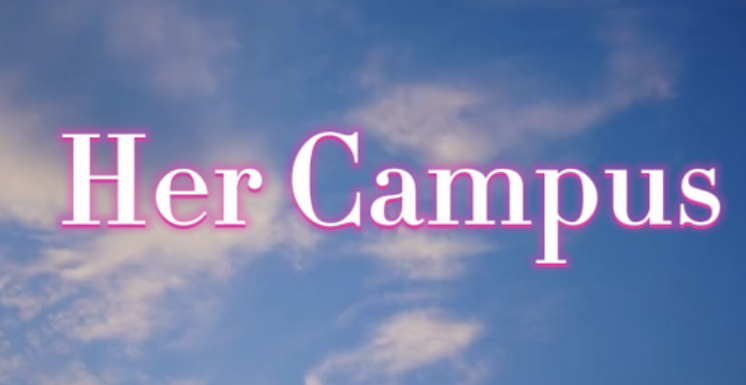
Font chữ Capcut này được nâng thẳng từ bìa tạp chí. Còn cách nào tốt hơn để liên kết thương hiệu của bạn với sự rung cảm thời trang cao cấp từ font chữ mang tên Vogue?
2. Nicolas Cochin LT Pro
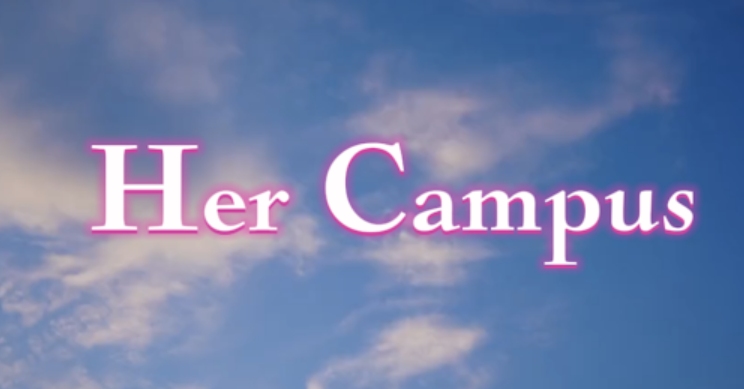
Font chữ này của Capcut mang đến cảm giác như một bộ phim Y2K các năm hai nghìn và phong cách này cũng đang trở lại xu hướng gần đây.
3. Brown Vokly
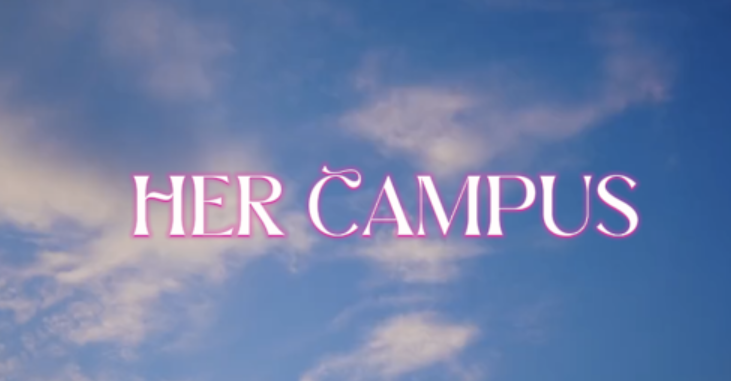
Lựa chọn tiếp theo này mang đến sực tinh tế . Đây là một lựa chọn hoàn hảo nếu phong cách của bạn thiên về khía cạnh thú vị và sôi nổi. Bên cạnh đó font chữ Capcut này vẫn cực kỳ dễ đọc trên màn hình nhỏ!
Những font chữ làm nổi bật câu chuyện
Tất cả chúng ta đều có câu chuyện cần được kể. Nhưng các video dài dòng có thể gặp bất lợi nghiêm trọng nếu không có lựa chọn font chữ phù hợp. Sau đây sẽ là những font chữ Capcut tạo ra sự cân bằng phù hợp bằng cách dễ nhìn nhưng vẫn cho phép một số cá tính tỏa sáng
1. It Clearface Pro
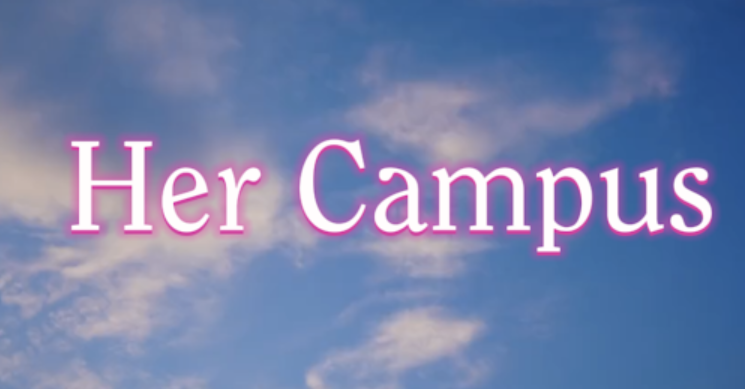
Font chữ Capcut này cực kỳ rõ ràng. Vì vậy nó sẽ không làm mất tập trung vào thông điệp của bạn nhưng vẫn tạo ấn tượng rằng bạn là người dễ gần và vui vẻ.
2. Shirkhand
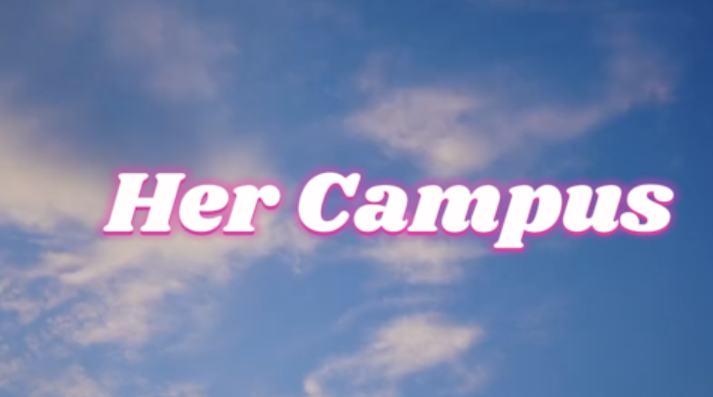
Tiếp theo là font chữ có tên Shirkhand thiên về khía cạnh sáng tạo. Bên cạnh đó font chữ này mang nét nữ tính tinh tế!
3. Helium
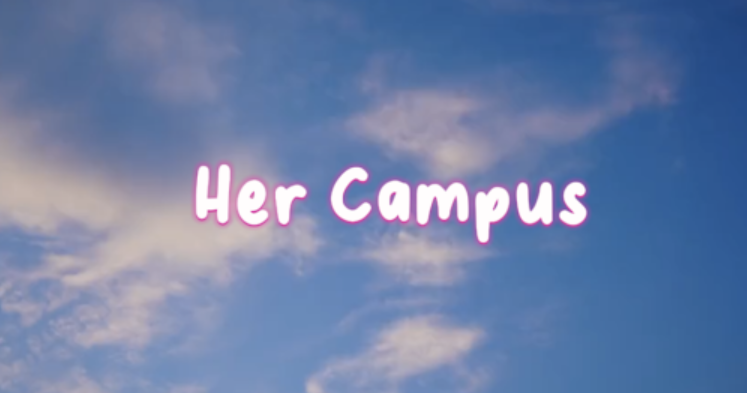
Đây là font chữ nhận được sự ưa chuộng của người dùng. Nó mang lại ấn tượng về chữ viết tay mà trông không quá trẻ con. Đây là một cách tuyệt vời để làm nội dung video có vẻ thực tế và hấp dẫn.
Font chữ mang cảm giác hồi hộp
Nếu bạn đang cố gắng thu hút đám đông trên TikTok, bạn có thể muốn thứ gì đó có thêm một chút gia vị. Hai font chữ Capcut sau đây sẽ khiến video của bạn không trở nên quá phô trương, nhưng lại bổ sung một lượng vừa đủ sự tinh tế.
1. LLD Techonological Glitch
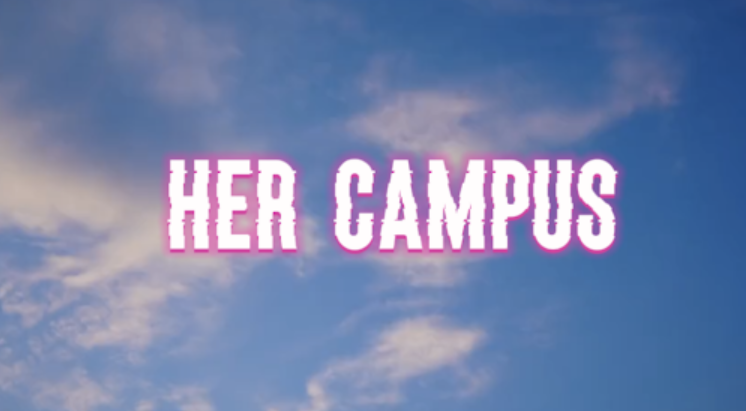
Font chữ này rất thú vị và sôi nổi. Phù hợp với tiêu đề hoặc phần giới thiệu. Sẽ thật tuyệt khi giới thiệu các video về lễ hội hoặc buổi hòa nhạc nào đó.
2. Got Heroin
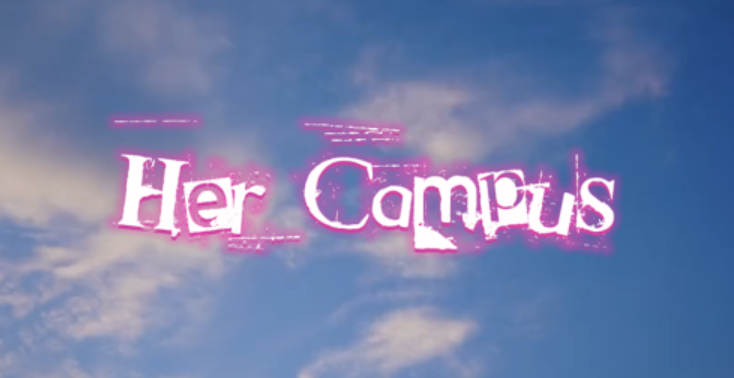
Nằm trong 8 font chữ Capcut mà bài viết muốn giới thiệu đến người dùng đó là font chữ Got Heorin. Tuy sẽ khá kén với một số chủ đề nội dung nhưng phong chữ này mang hoài niệm các tập chí Y2K đến người dùng.
Tất cả những font chữ này là gợi ý giúp bạn có thêm ý tưởng để làm video của mình. Tuy nhiên font chữ tốt nhất là font chữ bạn chọn. Hãy dành thêm vài phút trên Caput để tìm font chữ phù hợp với bạn và thể hiện thương hiệu cũng như cá tính riêng của bạn. Chúng có thể giúp làm cho video của bạn gắn kết hơn, dễ nhận biết hơn và quan trọng nhất là mang tính cá nhân.